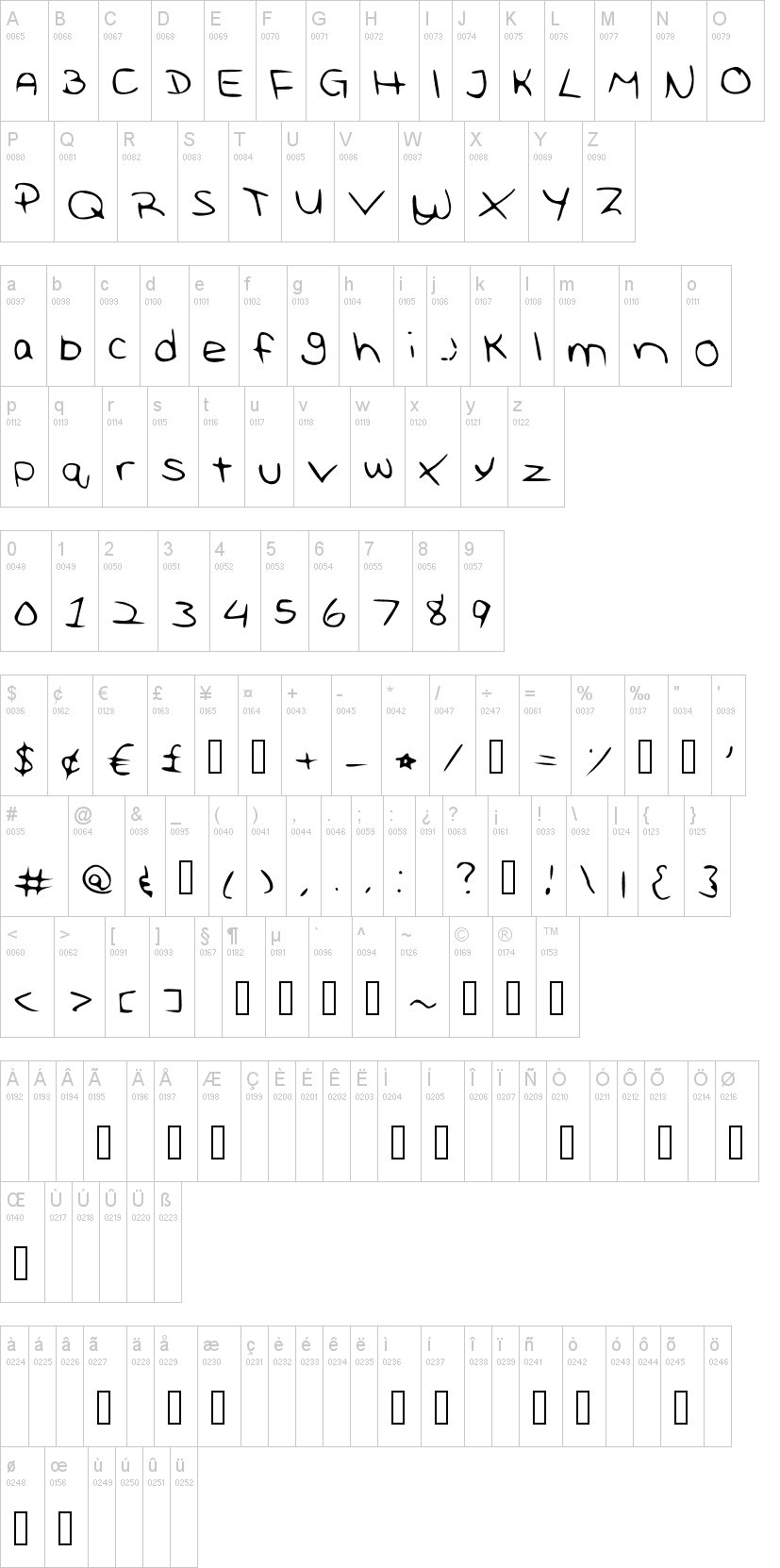
Rebecca's Handwriting是一款手写字体,由英国设计师Rebecca Alaccari创作。这款字体具有温暖、舒适的外观,整体风格轻松、活泼、富有表现力。它具有明亮的颜色,可以提供清晰流畅的文本,使用起来非常方便。此外,这款字体还具有良好的可读性,可以有效地传达消息,增强文本的可读性。另外,它还可以与其他字体搭配使用,以创造出更加有趣的设计效果。内容介绍
Rebeccas Handwriting是一款非常不错的手写艺术字体,具有很好的视觉感,适合于文化类的宣传设计、商业类品牌的广告和产品包装设计以及个性化文字排版等较多场景。